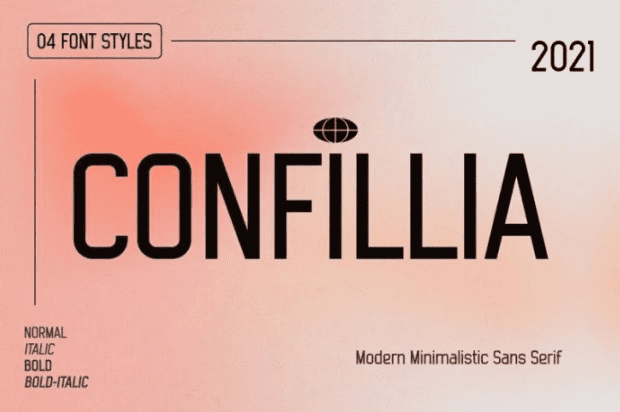
[Creativemarket] Confillia Font
Название: Confillia Font
[Creativemarket] Confillia Font
Вдохновленный вещами, связанными с чем-то современным, как сегодня, с высокими символами и доступными в 4-х типах, нормальный, курсив, жирный и жирный курсив.